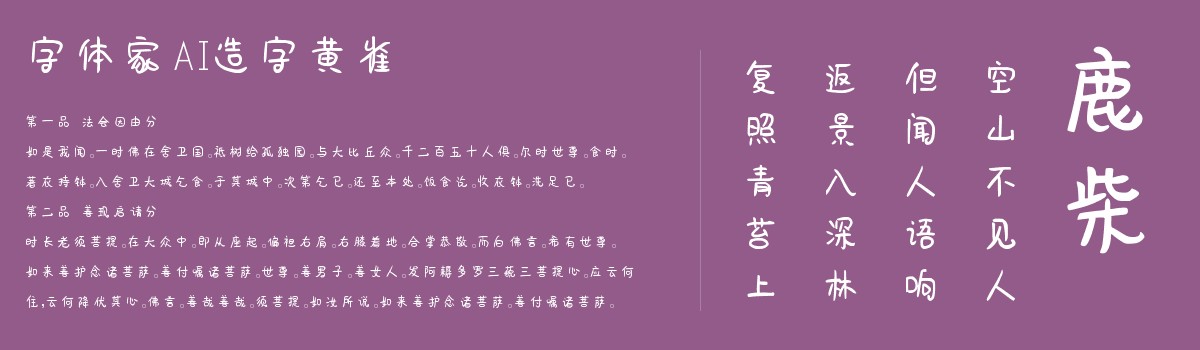
字体家AI造字黄雀
字体家AI造字黄雀是一款由字体家AI神笔造字生成的艺术字体,笔画粗细均匀,起笔收笔呈圆角,线条流畅柔和无尖锐棱角。字形方正饱满,结构舒展,重心平稳。笔画拐角处圆润过渡,无生硬折角,线条纯净无多余装饰。整体风格简约温润,兼具现代感与亲和力,给人平和舒适的触觉联想,如触摸打磨光滑的玉石,温润中透着规整。适合用于一些广告标题、平面文案、海报标题、网页广告用字的编辑。